年間定額制フォントサービス「LETS」20周年を記念して、合計51書体を提供開始
フォントワークスは、年間定額制フォントサービス『LETS』のリリース20周年を記念して、「フォントワークス LETS」「モトヤ lp/20th_anniversary」「YOON LETS」から合計51書体を、2022年9月26日(月)より提供を開始した。
年間定額制フォントサービス「LETS」
2002年からフォントワークスが提供している業界初の年間定額制フォントサービス「LETS(Leading Edge Type Solution)」。多彩なラインナップで、日本語、欧文、韓国語、簡体字、繁体字、タイ、ヘブライなどの各種フォントを提供している。今回追加される新書体は、「フォントワークスLETS」、「学生向けフォントワークスLETS」を契約中の会員であれば追加費用なく利用できる。
年間定額制フォントサービス「LETS」は2022年9月1日(木)にリリース20周年を迎えた。
フォントワークスLETSに新書体「あかかね」が登場
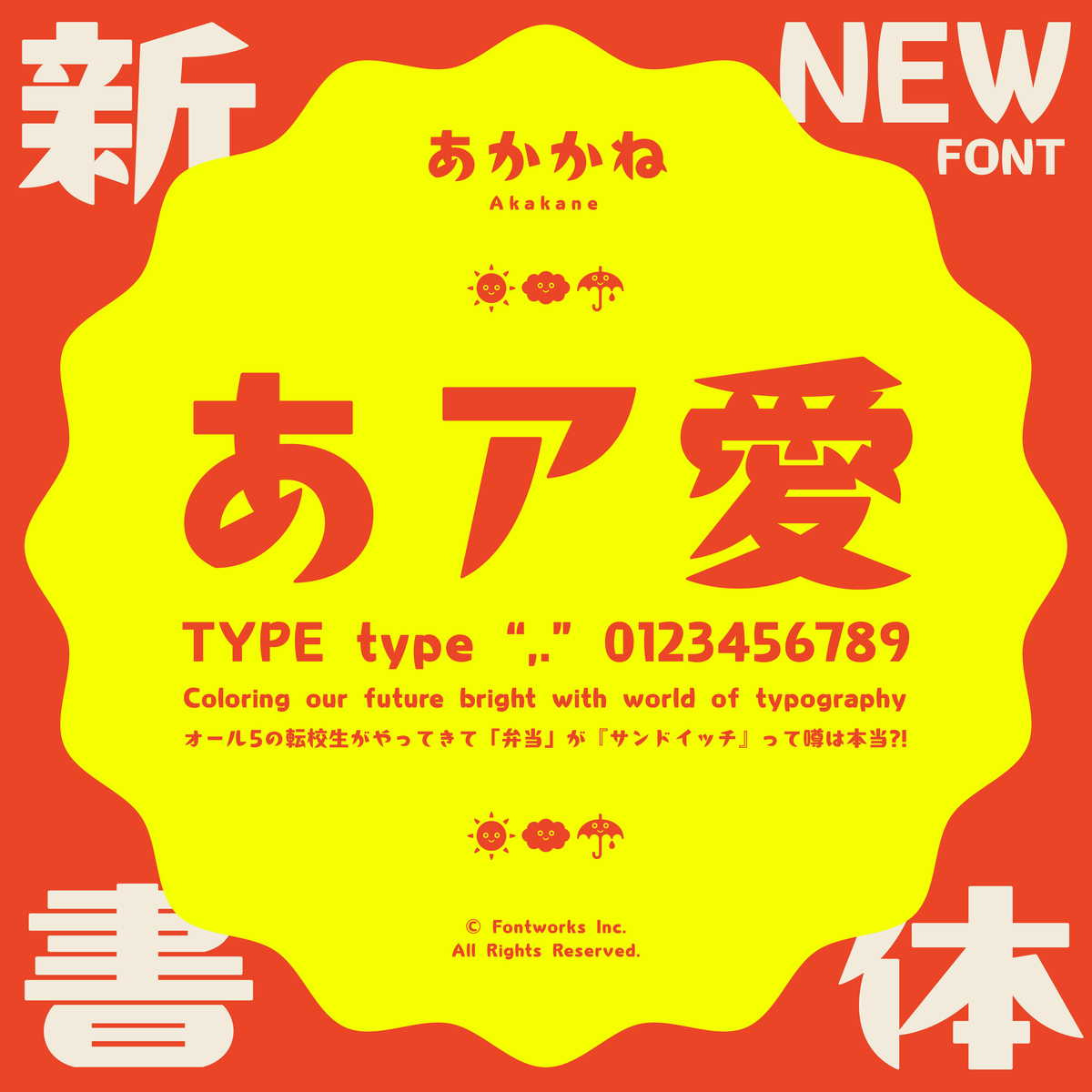
「フォントワークスLETS」から書体デザイナー・大崎善治氏による新書体「あかかね」が登場。
「あかかね」は、TV番組のテロップやポスター等で大人気の「くろかね」「あおかね」シリーズに続く最新作となる。
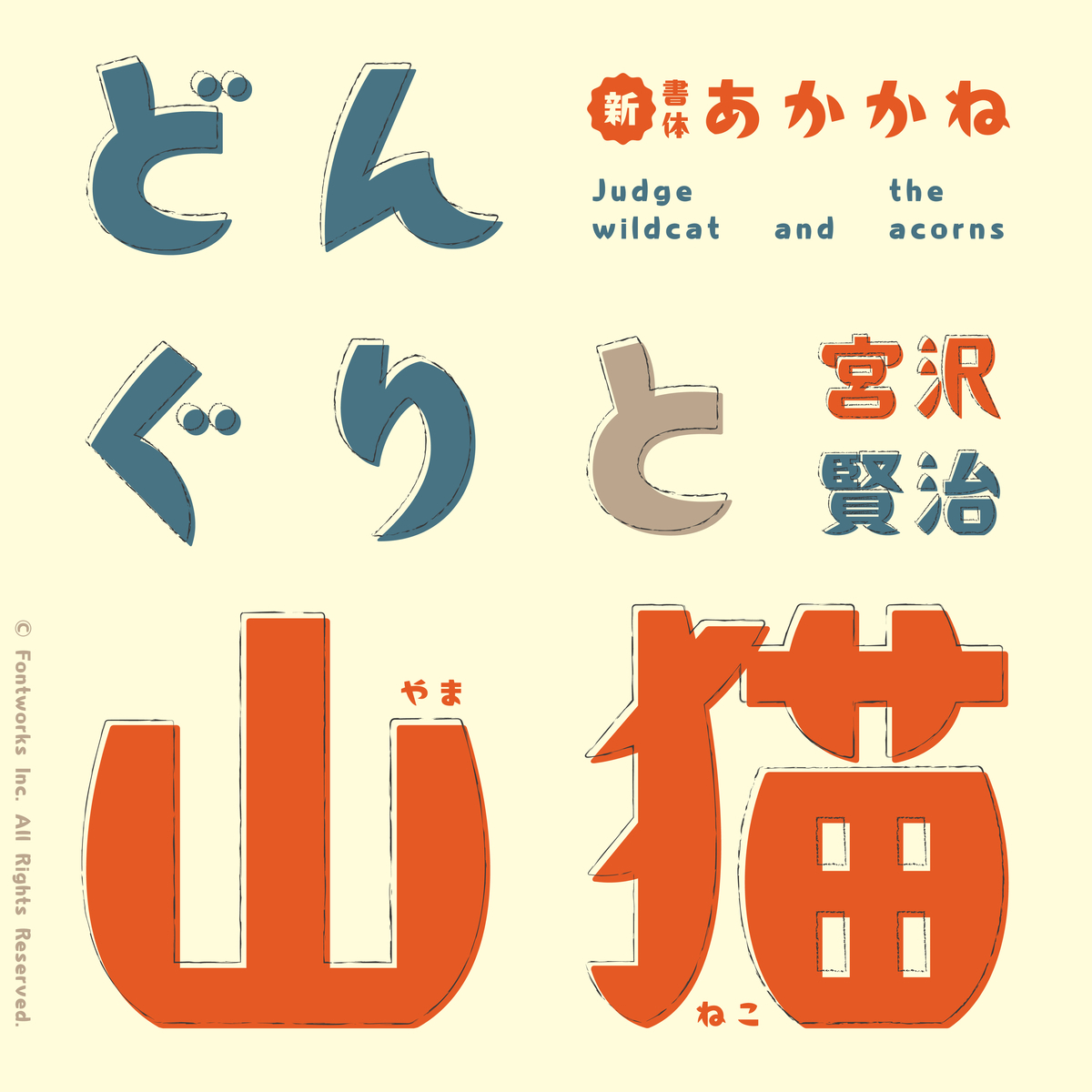
「あかかね」は、縦画と外側の丸みが特長の書体で、主張がありながらどこか素朴でかわいらしい印象を与える。
特に漢字は同じ部品でも字によって少しずつ印象が異なり、それぞれがユニークなキャラクター性を持つ。
視認性とデザイン性の両方をそなえ、様々なジャンルで使用できる。
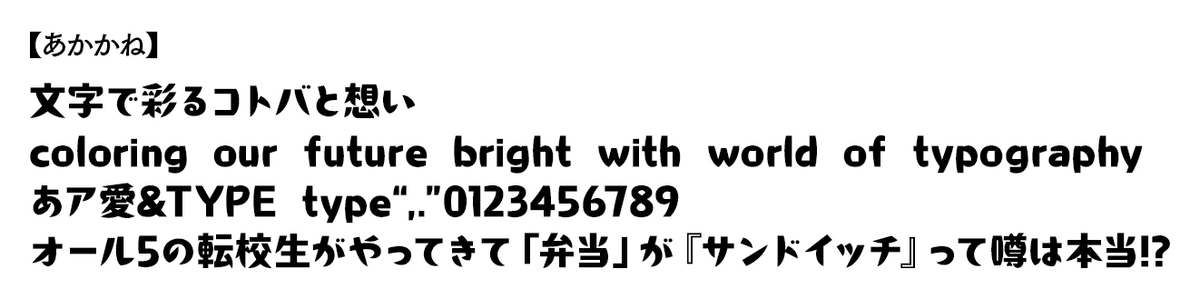
大崎善治Profile
書店勤務や写植オペおよびデザイン制作会社を経て、1999年よりフリーランスにて活動を開始。写植見本帳との出会いにより書体に興味を抱き、その後、数々の恵まれた出会いを重ね現在に至る。活版印刷を用いたタイポグラフィ作品から和文書体の制作と文字にまつわるデザインを幅広く行う。
フォントワークスLETSに「筑紫見出ミンシリーズ」文字セット拡張
提供中の「Std」に加え、「Pr6」「Pr6N」の文字セット拡張が行われた。
・筑紫A見出ミン Pr6 / Pr6N E
・筑紫B見出ミン Pr6 / Pr6N E
・筑紫C見出ミン Pr6 / Pr6N E
モトヤLETS
創業100周年を迎えた株式会社モトヤのフォントが使える「モトヤLETS」には、11書体が追加。
モトヤLETSに「モトヤ角ノート」にウエイト追加
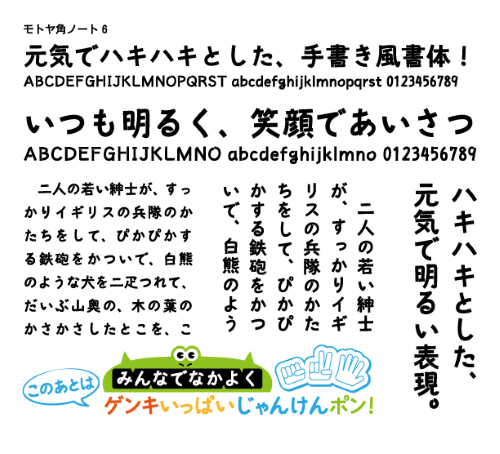
「モトヤ角ノート」に「W6」が追加され、2ウエイト展開となる。
モトヤLETSの「Sモトヤ正楷書5」「Sモトヤ新楷書5」文字セット拡張
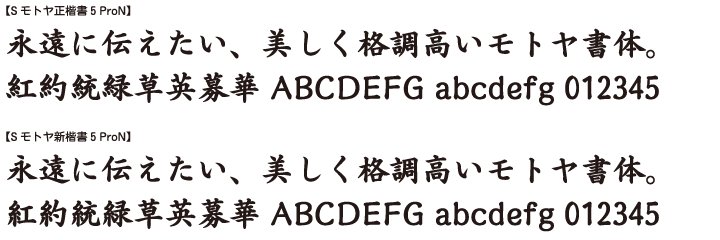
「Sモトヤ正楷書5」「Sモトヤ新楷書5」には、Pro仕様OpenTypeフォント(Adobe-Japan 1-4準拠)を追加。
モトヤLETSの「Pro仕様OpenTypeフォント(JIS90字形)」6書体に字形の追加・IVSの対応
「Pro仕様OpenTypeフォント(JIS90字形)」6書体に、新たにJIS2004字形(ProN)を追加。
また今回の仕様変更に併せて、Pro仕様OpenTypeフォント(ProN/Pro)でも異体字切り換え技術のIVS(異体字シーケンス)の対応を行った。
・Sモトヤ正楷書3 Pro / ProN
・Sモトヤ新楷書3 Pro / ProN
・モトヤ教科書2 Pro / ProN
・モトヤ教科書3 Pro / ProN
・モトヤ教科書4 Pro / ProN
・モトヤアンチック3 Pro / ProN
YOON LETS
韓国でトップシェアを誇る YoonDesign Group Inc. のフォントが使える「YOON LETS」からは、8ファミリー・33書体が登場。
本文に適した長体やゴシック体、キュートなデザインフォント、2002日韓ワールドカップスタジアム専用フォントなどを追加した。
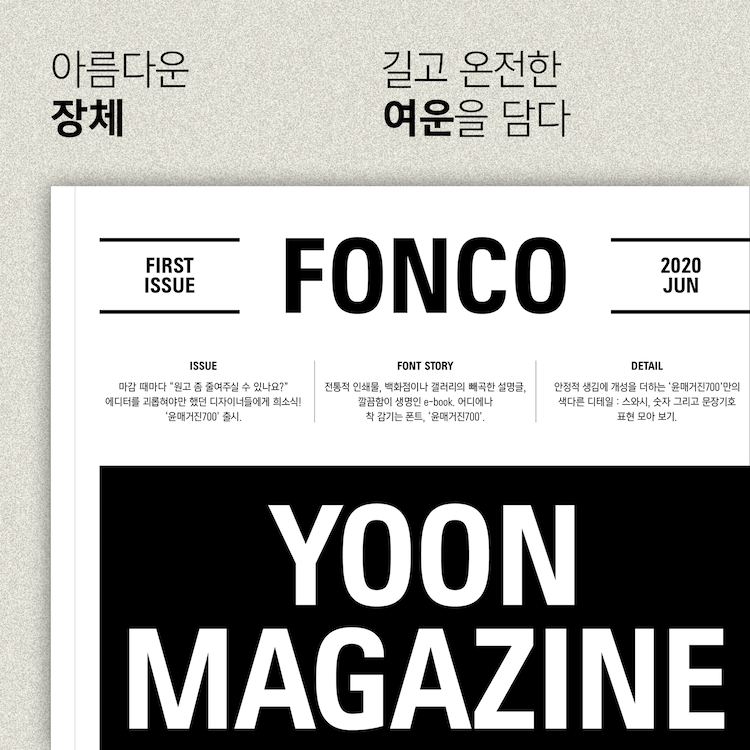
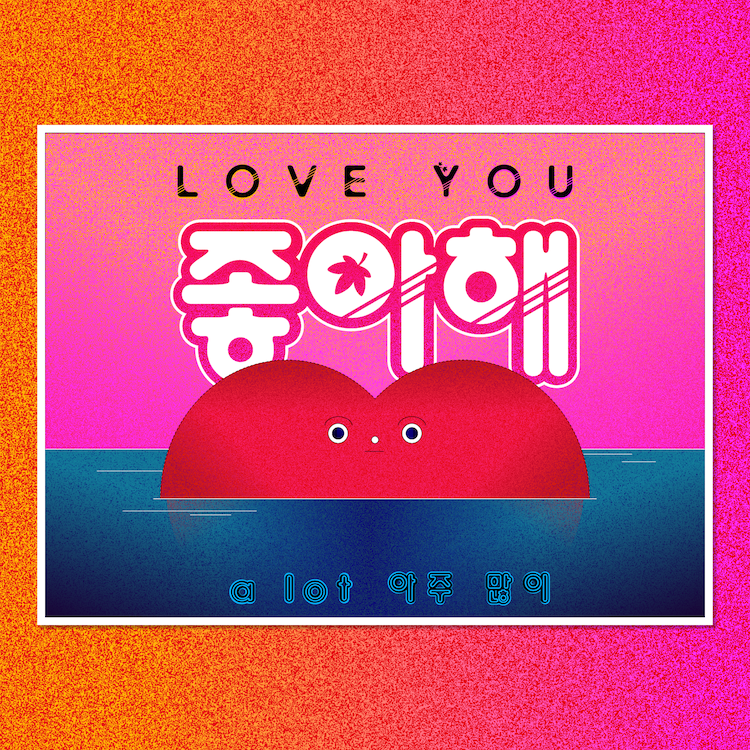
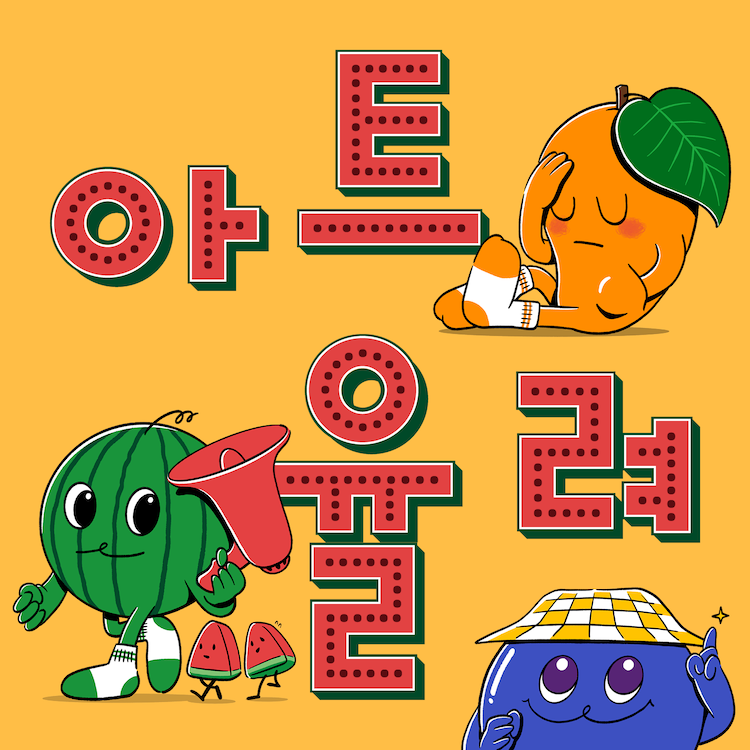
・Yoon Nunsongippumppum Style00 / Style01 / Style02 / Style03
・Yoon Sallanghanui Style00 / Style01 / Style02 / Style03
・Yoon SunShower B / M / L
・Yoon ArtYullyeo 3D / Dot / InLine / Original / outline / Shadow
・Yoon Magazine 710 / 720 / 730 / 740 / 750 / 760 / 770 / 80 / 790
・Yoon YoonGothic 520 / 530 / 540 / 550
・Yoon Solt B / L
・Yoon 2002